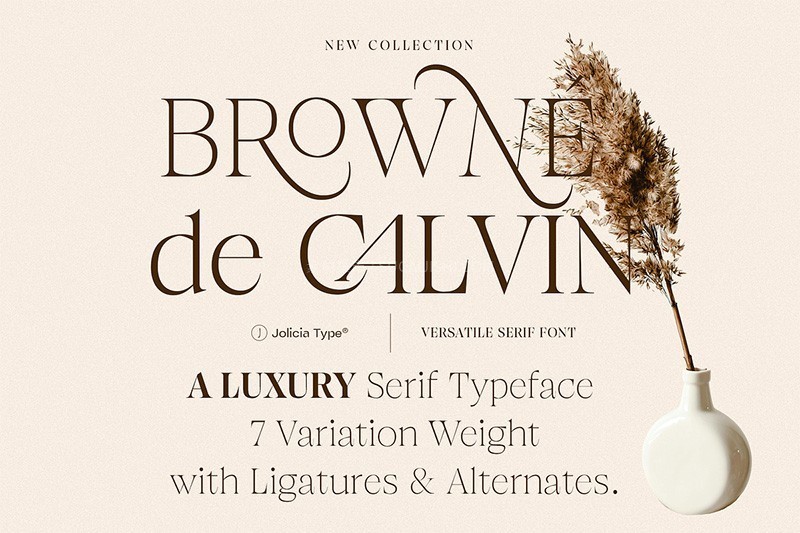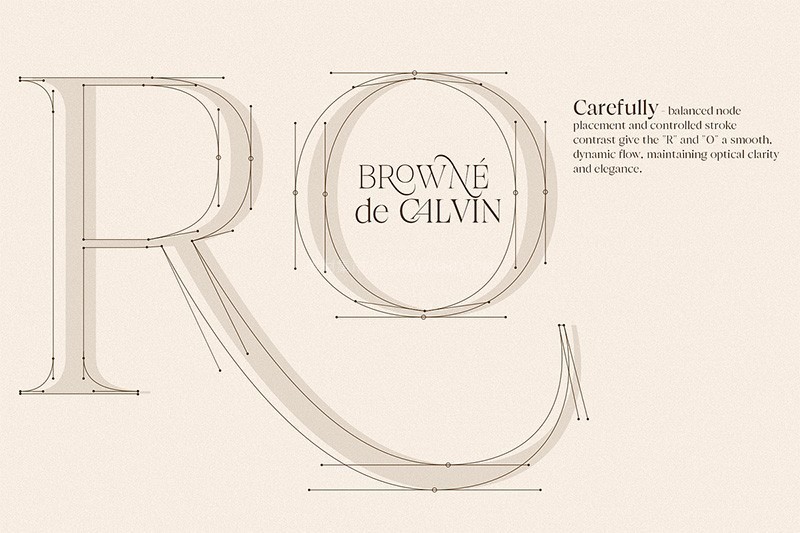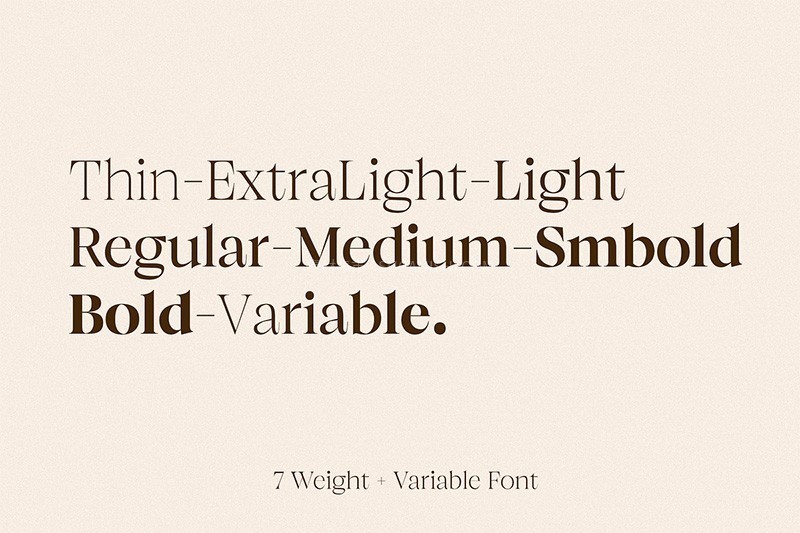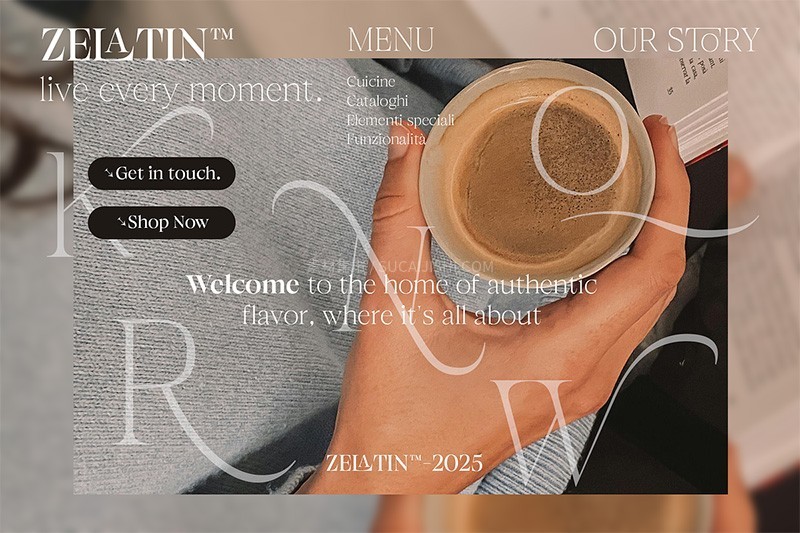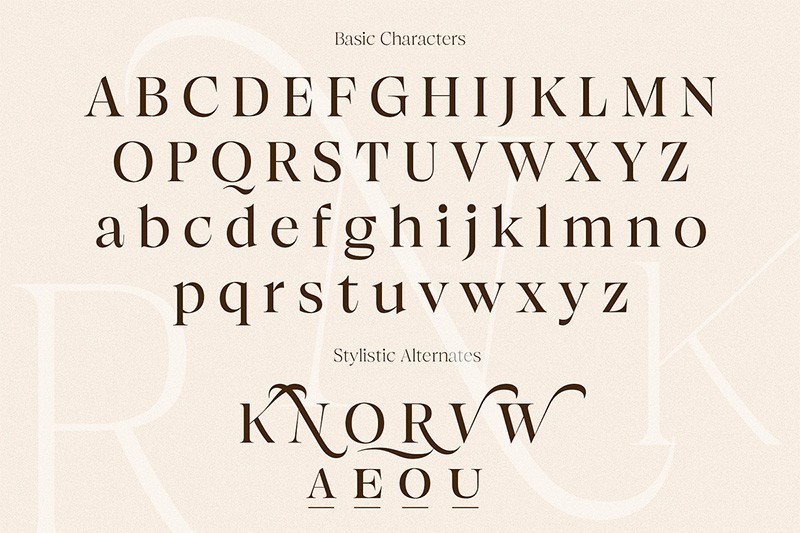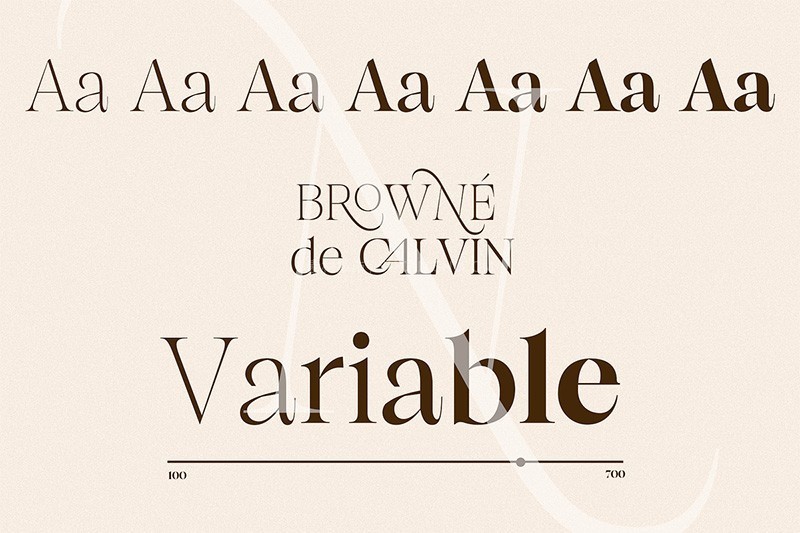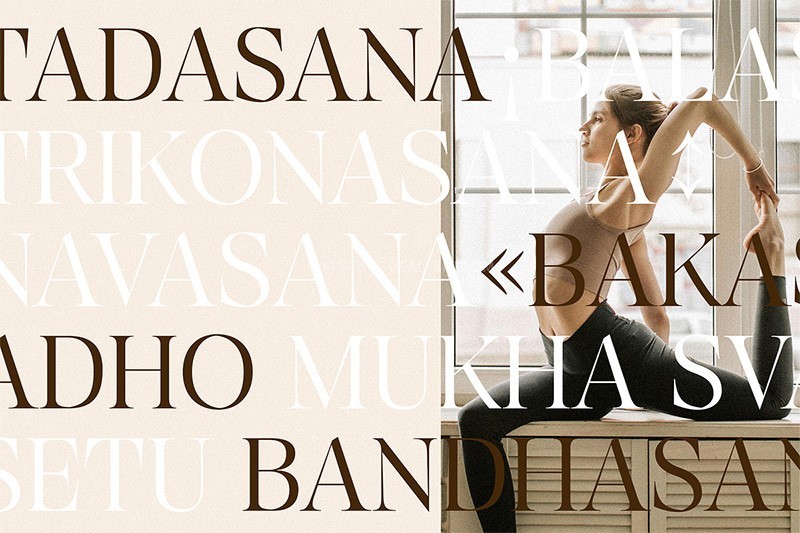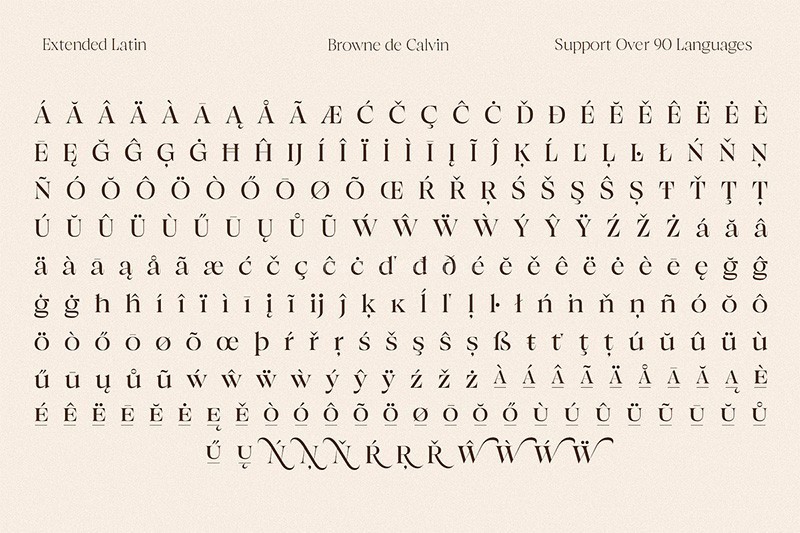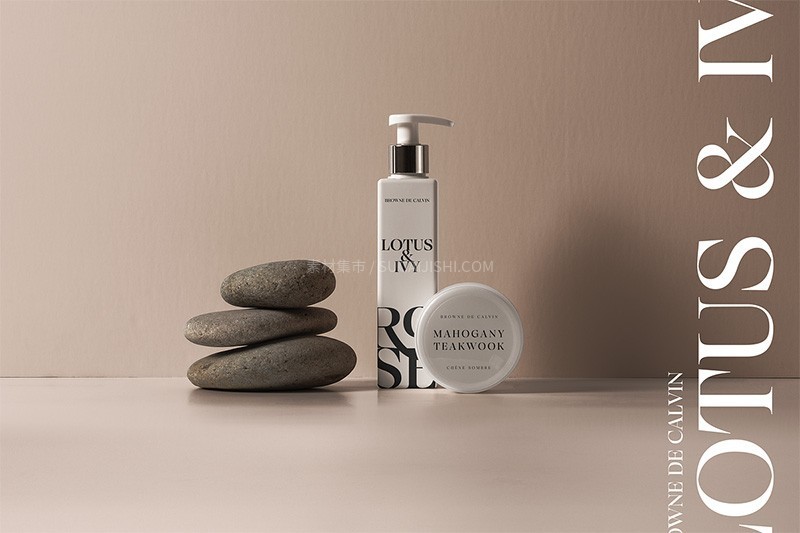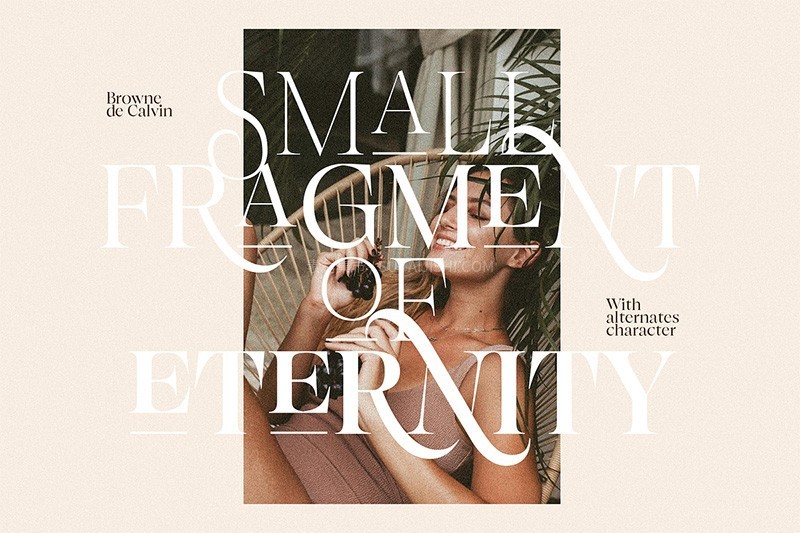
Browne de Calvin 是一款奢华的衬线字体,拥有精致优雅、精准考究的花体字风格。它提供 7 种字重选择,从细到粗,满足您对排版强度的不同需求。更棒的是,它还包含一个可变字体版本,让您能够无缝调整字重,实现精致到强烈的排版表达,完美契合您的视觉需求。这款字体将经典优雅与现代精致相结合,是高端品牌的首选。